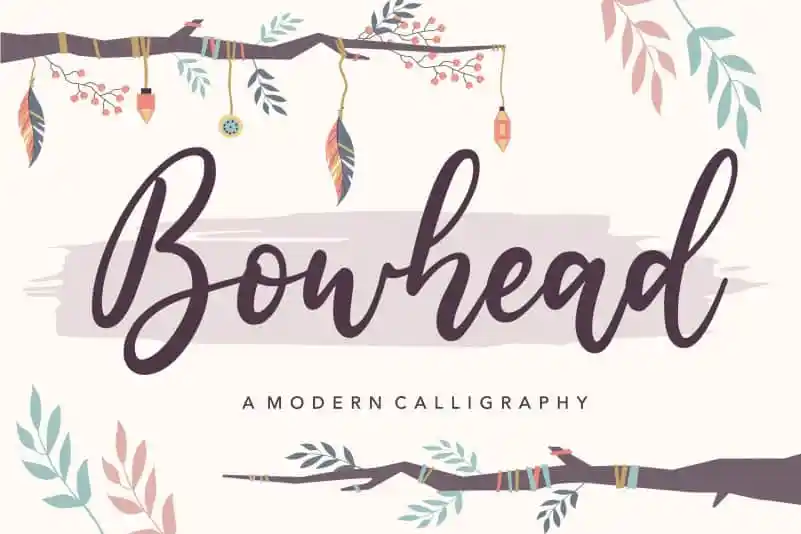
A fonte Bowhead Modern Calligraphy é perfeita para quem busca uma expressão moderna e elegante em sua criação visual. Este fonte suave possui linhas leves e fluidas, projetado para se destacar em vários ambientes gráficos, desde embalagens de produtos até a publicação de jornais e revistas. A ideia é também usar essa fonte nas redes sociais, em editoriais de wedding ou mesmo simplesmente sobreposto no fundo de um layout como uma maneira criativa de destacar o texto. Este moderno estilo calligrafico suave é perfeito para quem deseja manter seu design elegante e sofisticado, mas ainda permite uma personalização única e expressiva.